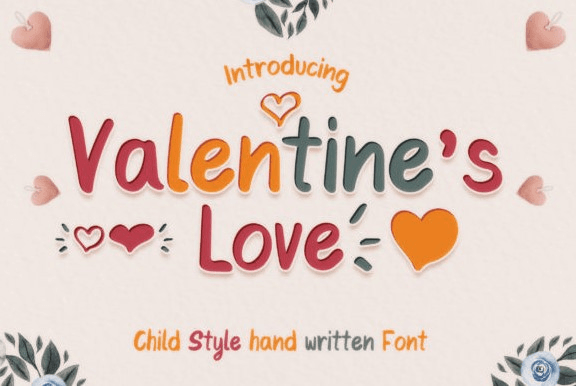
Valentine’s Love Font
Valentine's Love - это радостный и дружелюбный рукописный шрифт с милыми элементами каракули.
Влюбитесь в его сладкий, универсальный стиль и используйте его для создания прекрасных дизайнов для школы или детей, связанных с ним.
Valentine's Love - это радостный и дружелюбный рукописный шрифт с милыми элементами каракули.
Влюбитесь в его сладкий, универсальный стиль и используйте его для создания прекрасных дизайнов для школы или детей, связанных с ним.